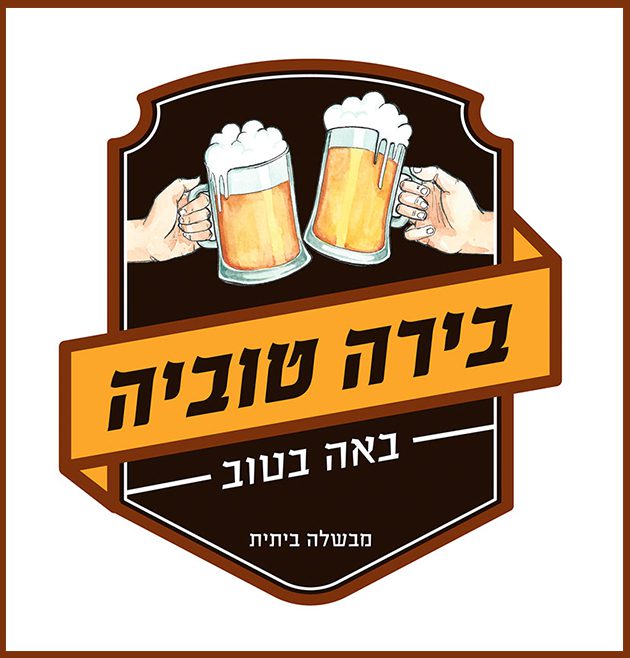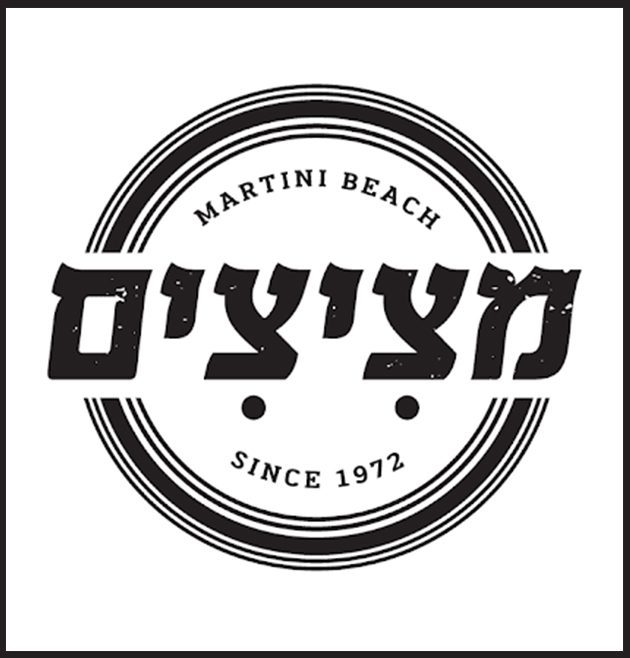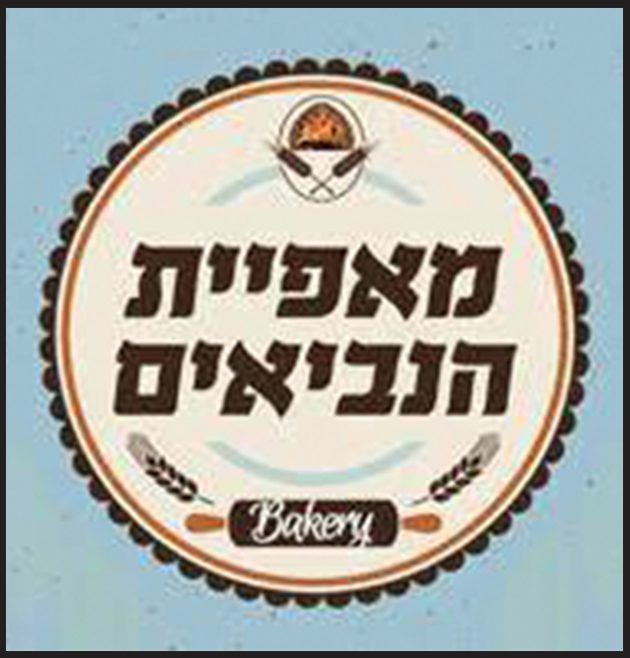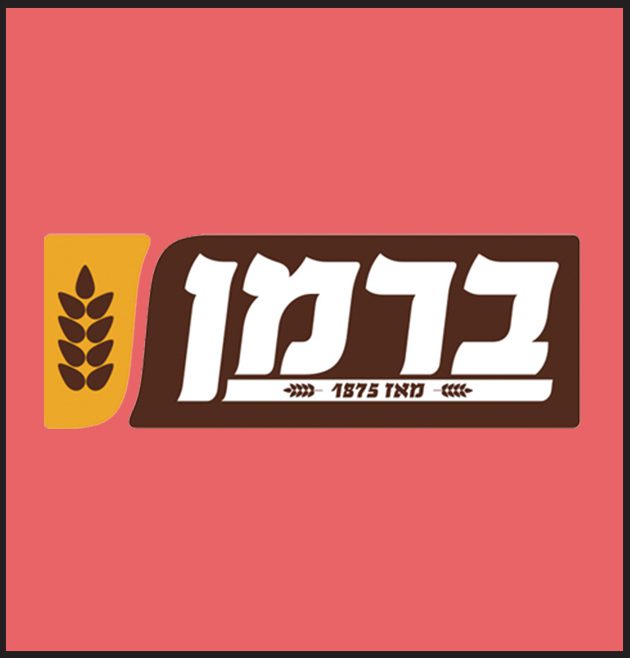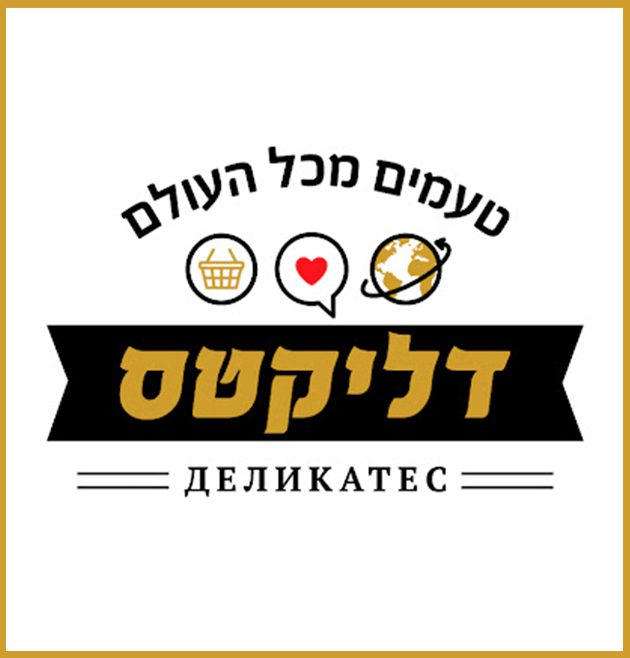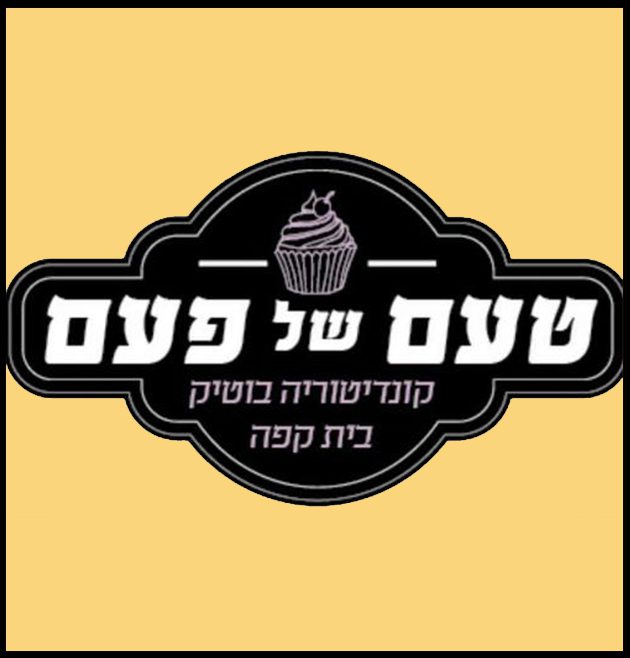
תפיסת העיצוב בפונטביט היא חופש וחדוות יצירה עם הערכה רבה למקור האלפבית העברי שמאכלס בתוכו מטען תרבותי רב-ערך. מטען זה מתבטא באופן בו התכונות לובשות צורה כאותיות המתקיימות יחד בהרמוניה. אות היא אמנם היחידה הקטנה והבסיסית ביותר במערך הטיפוגרפי השלם, אבל למרות מימדיה לאות יש השפעה משמעותית על המבנה החזותי של המילה, המשפט ולבסוף על תצורת הטקסט המעומד בשלמותו. פיתוח טיפוס אות, הינו תהליך של התגבשות הצורות וחיפוש אחר איזון בין התכונה של המבנה הכללי לבין התכונה הייחודית של כל אחת מהאותיות.
האלפבית העברי מאכלס בתוכו מטען תרבותי רב-ערך
ספריית פונטביט מעצבת דרך בתחום הטיפוגרפי מקצועי בישראל ומאגדת מגוון עשיר ומקורי של גופנים שימושיים. רמת גימור גבוהה, טווח שימוש מגוון וחיבור לשורשים העבריים, אלו קווי יסוד, עליהם נבנתה והתגבשה הספרייה. במהלך השנים הפכו הגופנים לחלק בלתי נפרד מהנוף הטיפוגרפי בישראל, מופיעים בכל המדיות ומתפקדים בעבודות מיתוג לרוב המוצרים בארץ. כך שעם הזמן, הפכו הגופנים למרכיב בסיסי והכרחי ב״תבשיל״.
מתבטא באופן בו התכונות לובשות צורה
ספריית פונטביט מעצבת דרך בתחום הטיפוגרפי מקצועי בישראל ומאגדת מגוון עשיר ומקורי של גופנים שימושיים. רמת גימור גבוהה, טווח שימוש מגוון וחיבור לשורשים העבריים, אלו קווי יסוד, עליהם נבנתה והתגבשה הספרייה. במהלך השנים הפכו הגופנים לחלק בלתי נפרד מהנוף הטיפוגרפי בישראל, מופיעים בכל המדיות ומתפקדים בעבודות מיתוג לרוב המוצרים בארץ. כך שעם הזמן, הפכו הגופנים למרכיב בסיסי והכרחי ב״תבשיל״.
מישראל אופי נוסטלגי